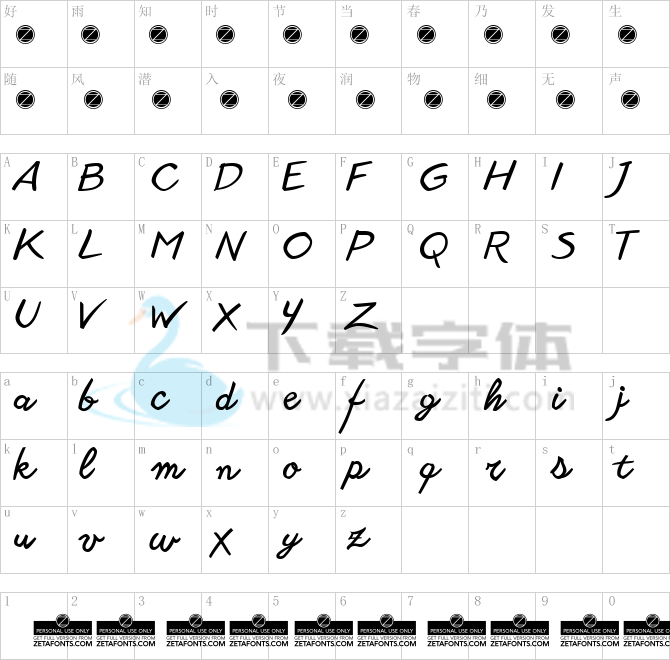
Another shabby.ttf字体下载
Another shabby.ttf字体下载,这款字体结构工整、笔画清晰,兼顾美观与易读性,适用于标题、正文、海报、包装、LOGO 等多种场景。字形优雅稳定,风格百搭耐看,适配日常排版与创意设计,让文字呈现更舒适、更具质感。Another shabby.ttf字体下载一笔一画,皆是细节,以均衡的比例、流畅的线条打造舒适视觉体验,字形端正大气,风格简约现代。无论是商业设计、品牌宣传还是日常排版,都能轻松驾驭,让文字更有格调与力量。Another shabby.ttf字体下载字体下载。